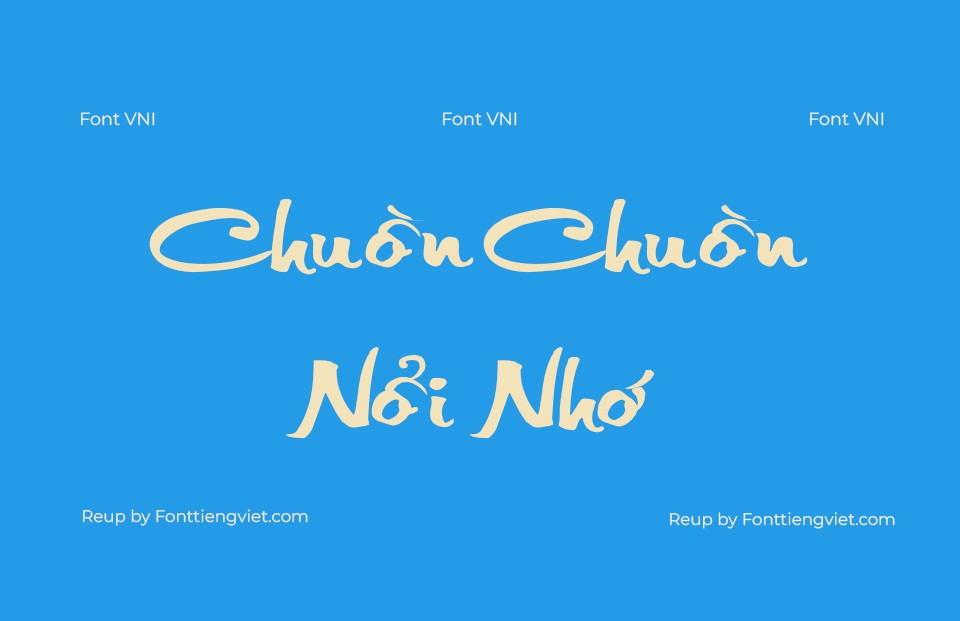
Trong thế giới đồ họa và thiết kế văn hóa, việc lựa chọn một Font Chữ phù hợp có vai trò vô cùng quan trọng, đặc biệt khi cần thể hiện sự trang trọng, nghệ thuật và đậm chất truyền thống Việt Nam.
Một trong những lựa chọn hàng đầu được giới thiết kế và học sinh, sinh viên yêu thích chính là Font Việt hoá VNI Thuphap3.
Đây không chỉ là một phông chữ đơn thuần mà còn là một tác phẩm nghệ thuật số, mô phỏng hoàn hảo nét bút uyển chuyển của thư pháp Việt, mang lại linh hồn cho mọi ấn phẩm từ báo tường, kỷ yếu cho đến các dự án nghiên cứu lịch sử.
Font Việt hoá VNI Thuphap3: Công Cụ Thiết Yếu Cho Đồ Họa Học Đường
Sự ra đời của Font Việt hoá VNI Thuphap3 đã giải quyết triệt để vấn đề hiển thị ký tự tiếng Việt chuẩn mực trong các thiết kế mang tính nghệ thuật.
Trước đây, các font thư pháp nước ngoài thường không hỗ trợ đầy đủ dấu tiếng Việt, gây ra lỗi hiển thị hoặc yêu cầu tinh chỉnh phức tạp.
Nhờ quá trình Việt hoá tỉ mỉ, font VNI Thuphap3 đảm bảo rằng mọi ký tự, từ chữ cái đến dấu thanh, đều được hiển thị một cách trôi chảy và hài hòa, giữ nguyên được vẻ đẹp thư pháp truyền thống.
Điều này đặc biệt hữu ích cho các bạn học sinh, sinh viên đang chuẩn bị cho các bài thuyết trình quan trọng, các dự án cuối kỳ hay thậm chí là thiết kế thiệp chúc mừng mùa thi cử, giúp bài làm đạt được tính thẩm mỹ cao nhất.
Đặc Điểm Nổi Bật Của Bộ Font Thuphap3
Thuphap3 là một thành viên tiêu biểu trong nhóm font thư pháp VNI.
Điểm mạnh nhất của nó là khả năng mô phỏng nét bút lông một cách chân thực, với các đường cong mềm mại, thanh đậm rõ ràng và sự bay bổng ở các đầu nét.
Đây là yếu tố quyết định tạo nên sự khác biệt so với các font in thường, mang đến cảm giác thủ công, tinh tế cho người xem.
Các nhà thiết kế thường lựa chọn font này khi cần tạo ra sự kết nối mạnh mẽ với văn hóa dân tộc.
Đối với các dự án học tập liên quan đến Lịch sử, Ngữ văn hoặc Giáo dục công dân, việc sử dụng Font Việt hoá VNI Thuphap3 giúp tăng cường tính thuyết phục và nghệ thuật của nội dung trình bày.
Ứng Dụng Thực Tế Trong Môi Trường Học Đường và Chuẩn Bị Thi Tốt Nghiệp
Trong quá trình học tập, đặc biệt là giai đoạn chuẩn bị cho các kỳ thi quan trọng hay các buổi lễ tốt nghiệp, nhu cầu về tài liệu in ấn và thiết kế chuyên nghiệp tăng cao.
Font Thuphap3 được ứng dụng rộng rãi để:
- Thiết kế Báo tường: Tạo tiêu đề ấn tượng, thu hút sự chú ý.
- Làm Kỷ yếu Tốt nghiệp: Đưa vào các trang lời ngỏ, lời cảm ơn để tăng tính trang trọng.
- Trang trí Tiêu đề Slide Thuyết trình: Giúp các bài giảng môn xã hội trở nên sinh động và đậm chất văn hóa hơn.
- In ấn Giấy khen, Chứng chỉ: Góp phần làm tăng giá trị nghệ thuật của tài liệu được trao tặng.
Sự kết hợp giữa yếu tố Việt hoá chuẩn mực và phong cách thư pháp cổ điển làm cho phông chữ này trở thành cầu nối giữa truyền thống và công nghệ hiện đại.
Việc nắm vững cách sử dụng các font như Font Việt hoá VNI Thuphap3 cũng là một kỹ năng hữu ích, giúp học sinh, sinh viên phát triển khả năng trình bày và tư duy thiết kế cơ bản, mở ra nhiều cơ hội trong các lĩnh vực sáng tạo sau này.
Tóm lại, Font Việt hoá VNI Thuphap3 là một tài sản quý giá trong bộ sưu tập font dành cho người Việt, đặc biệt là những người làm công tác giáo dục và thiết kế sáng tạo.
Sự kết hợp giữa tính nghệ thuật cao và khả năng Việt hoá hoàn hảo khiến nó trở thành lựa chọn không thể thiếu cho các dự án cần sự trang trọng, truyền thống.
Việc làm chủ loại Font Chữ đặc biệt này chắc chắn sẽ nâng tầm chất lượng các ấn phẩm học đường và chuyên nghiệp của bạn lên một đẳng cấp mới.